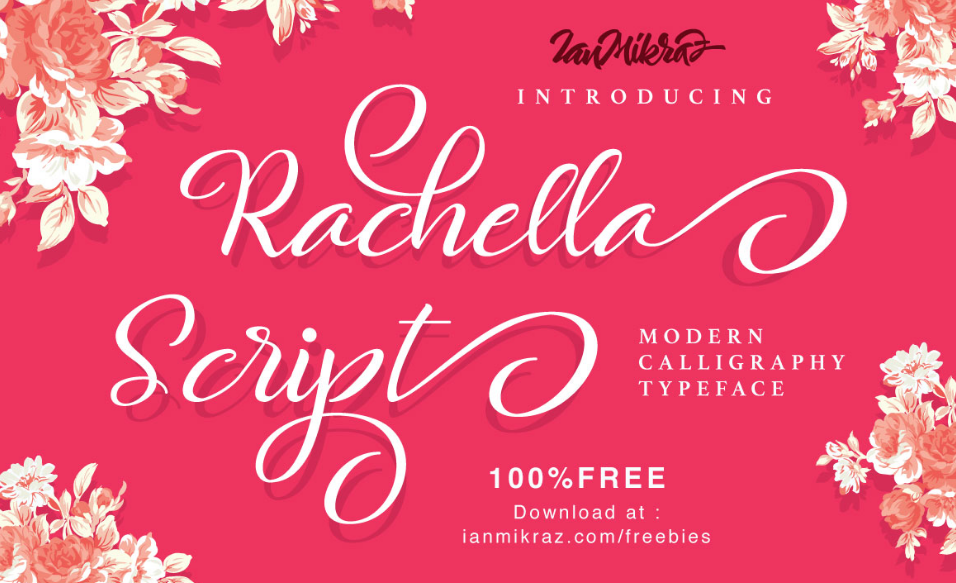
Rachella Script Font – Download Grátis
A Rachella Script Font é uma nova coleção de fontes tipográficas que vem da Ianmikraz Studio, combinando influências do caleidoscópio à tipografia contemporânea, elementos clássicos e um toque elegante e poético. Criada pelo designer Ianmikraz, essa fonte traz uma atmosfera de riqueza e modernidade ao seu design. Inspirada no estilismo da caligrafia, a Rachella Script Free Typeface é como se ela surgisse de um primeiro olhar apaixonado pela arte da escrita, desenhando-se em uma mistura única de elegância e frescura. Esta fonte é ideal para quem busca uma combinação versátil entre a delicadeza tradicional e o refinamento moderno, tornando-a perfeita para trabalhos que valorizam tanto a história quanto o futuro da tipografia. A Ianmikraz Studio oferece não apenas um design único, mas também uma paixão pelo universo do tipo, mantendo a fonte como um presente contínuo de arte e inspiração para quem deseja incorporar elementos únicos e estilizados em seus projetos.